Trong lĩnh vực thiết kế, việc lựa chọn font chữ phù hợp có thể tạo ra sự khác biệt lớn trong việc truyền tải thông điệp và phong cách của một sản phẩm. Font chữ UTM là một trong những bộ font chữ được yêu thích và sử dụng rộng rãi trong cộng đồng thiết kế Việt Nam. Bộ font này không chỉ đa dạng về kiểu dáng mà còn mang đến cho người dùng nhiều lựa chọn từ chữ ký viết tay, chữ văn bản đến chữ in hoa cứng cáp mạnh mẽ. Bài viết này sẽ giới thiệu đến bạn full bộ font chữ UTM giúp nâng tầm thiết kế của bạn.
Font chữ UTM, viết tắt của Unicode Thiên Minh, là một bộ font được thiết kế đặc biệt để hỗ trợ gõ tiếng Việt một cách hiệu quả và chính xác. Đặc điểm nổi bật của bộ font UTM
Hỗ trợ tiếng Việt hoàn hảo: Nhờ vào việc tuân theo chuẩn Unicode, font UTM đảm bảo mọi ký tự tiếng Việt, bao gồm cả các dấu thanh và chữ cái đặc biệt, đều được hiển thị chính xác.
Đa dạng và phong phú: Bộ font UTM bao gồm nhiều kiểu chữ khác nhau, từ đơn giản, tinh tế đến phức tạp, nghệ thuật. Điều này tạo điều kiện cho người dùng lựa chọn phong cách phù hợp với từng loại tài liệu hay mục đích sử dụng.
Khả năng tương thích cao: Không chỉ hoạt động tốt trên các nền tảng khác nhau như Windows, MacOS, mà UTM còn tương thích với hầu hết các phần mềm thiết kế và soạn thảo văn bản hiện nay.
Bộ font UTM là một trong những bộ font phổ biến và được yêu thích trong thiết kế tại Việt Nam. Dưới đây là một số nhóm kiểu chữ chính trong bộ font UTM.
Nhóm chữ ký UTM viết tay mềm mại bao gồm những kiểu chữ mang lại cảm giác tự nhiên, gần gũi và cá nhân. Những kiểu chữ này thường được sử dụng trong các thiết kế cần sự ấm áp, thân thiện như thiệp mời, bìa sách hoặc các sản phẩm thủ công. Chúng thường có những đường nét uốn lượn, mềm mại, tạo cảm giác như được viết bằng tay.
Nhóm font chữ UTM có chân, hay còn gọi là Serif, thường được sử dụng trong các văn bản chính thống như báo chí, sách giáo khoa và tài liệu học thuật. Đặc điểm của nhóm chữ này là các nét chữ có thêm phần chân, tạo ra sự rõ ràng và dễ đọc trong các văn bản dài.
Khác với nhóm font chữ UTM có chân, font chữ UTM không chân (Sans-serif) mang đến cảm giác hiện đại và tối giản. Những kiểu chữ này thường được sử dụng trong các thiết kế hiện đại, quảng cáo và trên các nền tảng kỹ thuật số do tính dễ đọc và phong cách trẻ trung của chúng.
Nhóm font chữ UTM văn bản được thiết kế để tối ưu hóa sự dễ đọc và rõ ràng, đặc biệt trong các đoạn văn bản dài. Chúng thường có kích thước và khoảng cách giữa các chữ cái hợp lý, giúp người đọc dễ dàng theo dõi và không bị mỏi mắt khi đọc lâu.
Bộ font UTM không chỉ đa dạng về kiểu dáng mà còn mang đến cho người dùng nhiều lựa chọn phù hợp với các mục đích sử dụng khác nhau, từ thiết kế đồ họa đến biên tập văn bản. Dưới đây là một số font chữ nổi bật trong bộ font này mà bạn có thể tham khảo.
UTM Roman Classic là một font chữ có chân mang phong cách hiện đại, phù hợp với nhiều loại văn bản và thiết kế. Với những đường nét sắc sảo và gọn gàng, font chữ này mang lại cảm giác chuyên nghiệp và tinh tế. UTM Roman Classic thường được sử dụng trong các tác phẩm in ấn như sách báo, tài liệu học tập hay thậm chí trong các thiết kế quảng cáo. Sự cân đối giữa các chữ cái giúp cho văn bản trở nên dễ đọc và dễ nhìn.
UTM BryantLG là một font chữ mang phong cách hoạt hình đáng yêu, phù hợp với những thiết kế vui nhộn và sáng tạo. Với các nét chữ tròn trịa và mềm mại, font chữ này giúp cho các sản phẩm thiết kế trở nên sinh động và hấp dẫn hơn. UTM BryantLG thường được sử dụng trong các tài liệu dành cho trẻ em, thiệp chúc mừng hoặc các trang trí mang tính chất vui tươi và nhẹ nhàng.
UTM Facebook K&T là một font chữ cứng cáp, mạnh mẽ, thường được sử dụng trong các thiết kế cần tạo ấn tượng mạnh. Với các nét chữ đậm và chắc chắn, font chữ này giúp làm nổi bật thông tin quan trọng, thu hút sự chú ý của người đọc. UTM Facebook K&T thường được sử dụng trên các biểu ngữ, poster sự kiện hoặc các sản phẩm thiết kế cần sự nổi bật và sáng tạo.
UTM A&S Heartbeat là một font chữ viết tay mềm mại, mang đến cảm giác nhẹ nhàng và lãng mạn. Font chữ này thường được sử dụng trong các thiết kế thiệp mời, thiệp chúc mừng hoặc các ấn phẩm cần sự gần gũi và thân thiện. Với những nét chữ uyển chuyển và mềm mại, UTM A&S Heartbeat giúp tạo nên một không gian thiết kế đầy nghệ thuật và cảm xúc.
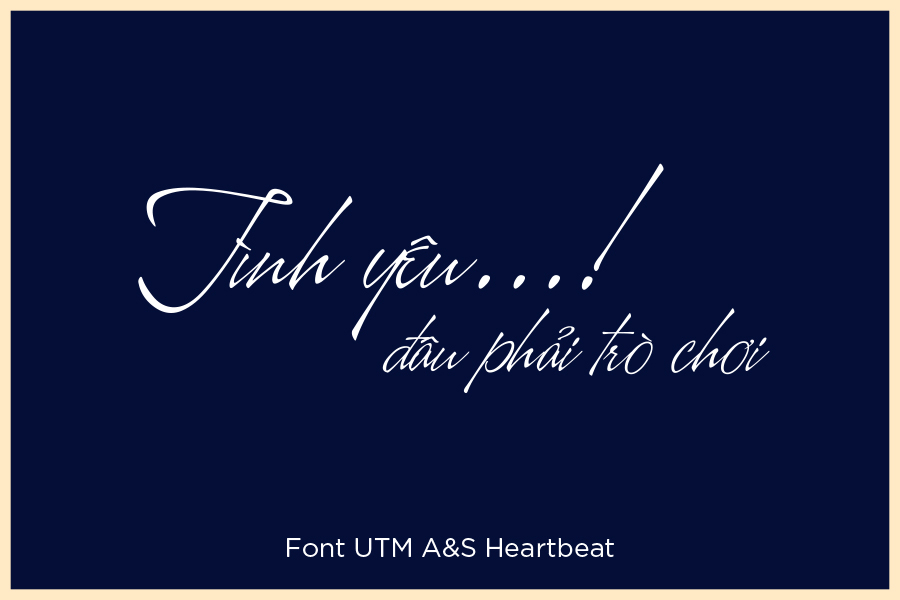
UTM Iron Gothic là một font chữ mang phong cách lịch sử, cổ điển, thường được sử dụng trong các thiết kế mang tính chất trang trọng, văn hóa. Với các nét chữ đậm, font chữ này gợi nhớ đến những văn bản cổ xưa và các công trình kiến trúc lịch sử. UTM Iron Gothic thường được sử dụng trong các tài liệu lịch sử, biển hiệu cổ điển hoặc các tác phẩm nghệ thuật cần sự chững chạc và trang nghiêm.
Có thể thấy, bộ font UTM mang đến cho bạn những kiểu chữ đa dạng và phong phú, giúp bạn tự do sáng tạo trong thiết kế.
Bộ font chữ UTM không chỉ đa dạng về kiểu dáng mà còn mang đến cho người dùng nhiều lựa chọn từ chữ ký viết tay, chữ văn bản đến chữ in hoa cứng cáp mạnh mẽ. Những font chữ này không chỉ giúp nâng tầm thiết kế mà còn mang đến sự sáng tạo và phong cách riêng cho mỗi sản phẩm.